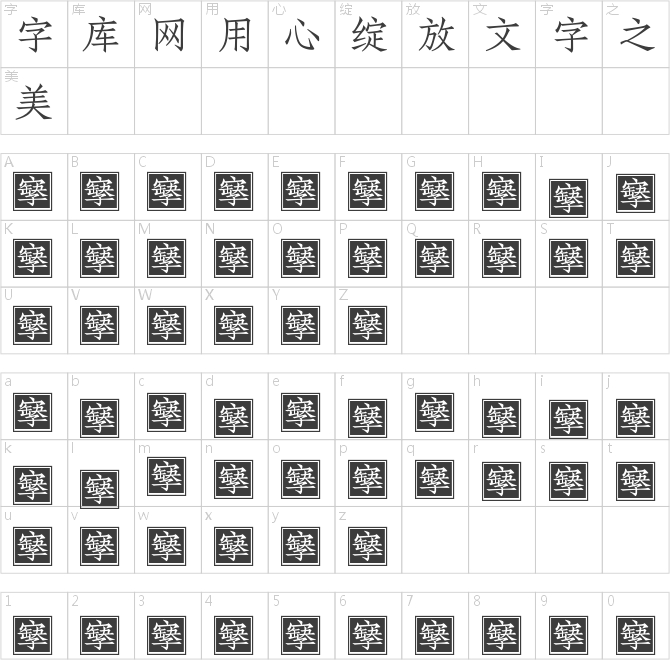
字體名稱: 朱雀仿宋
作者版權: 璇璣造字
朱雀仿宋
朱雀仿宋介紹
「朱雀仿宋」改刻自民國活字「南宋」,試圖為這套沉睡數十年的字體賦予新生。「南宋」是 1932 年「百宋書局」推出的仿宋體活字,韓佑之設計原稿,鄒根培雕刻字模。一經面世,即廣泛用于書籍、期刊排印。「南宋」與大多數正文字體的設定不同的是,它中宮收緊,重心略靠右下,撇捺舒展,筆畫的粗細變化強烈,含蓄秀美而充滿力量感,在排印標題和正文時展現出濃厚的「書卷氣」。
在「南宋」活字的基礎上,「朱雀仿宋」稍稍削弱了筆畫的對比度,適當地規整了字形結構與版面效果,同時最大程度地保留了「南宋」的獨特氣質與活字趣味。
「朱雀」是中國傳統文化中「四象」之一,南方七宿之神。以「朱雀」為名,暗合了「南宋」淵源與「璇璣造字」的品牌名。
• 孫明遠:《中國近現代平面設計和文字設計發展歷程研究——從一八〇五年至一九四九年》,廈門大學出版社,2021 年第 1 版,第 168~172 頁
• 周博:《中國現代文字設計圖史》,北京大學出版社,2018 年第 1 版,第 122~124 頁
「朱雀」團隊
主創:余俊益
假名與符號(制作中):韓泳思技術:殷葉航、余俊益